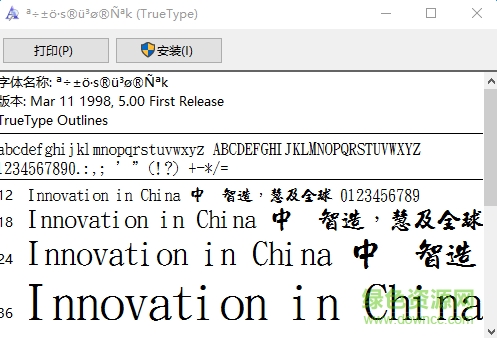
金梅新海報(bào)書法
金梅新海報(bào)書法字體是一款很有實(shí)用的繁體電腦字體,這款字體寫出來的字是很好看的,筆畫粗細(xì)均勻,又有點(diǎn)小活潑,可以用于書畫寫作方面,喜歡這款字體的朋友就快來綠色資源網(wǎng)下載吧。
金梅新海報(bào)書法字體就像它的名字一樣是一款書法字體,寫出來的字蒼勁有力,大氣磅礴,大家可以將這款字體用在很多方面,比如廣告設(shè)計(jì)就很不錯(cuò)啊。